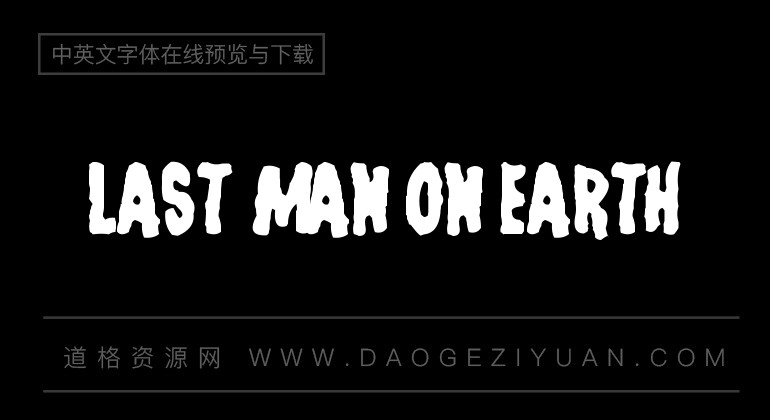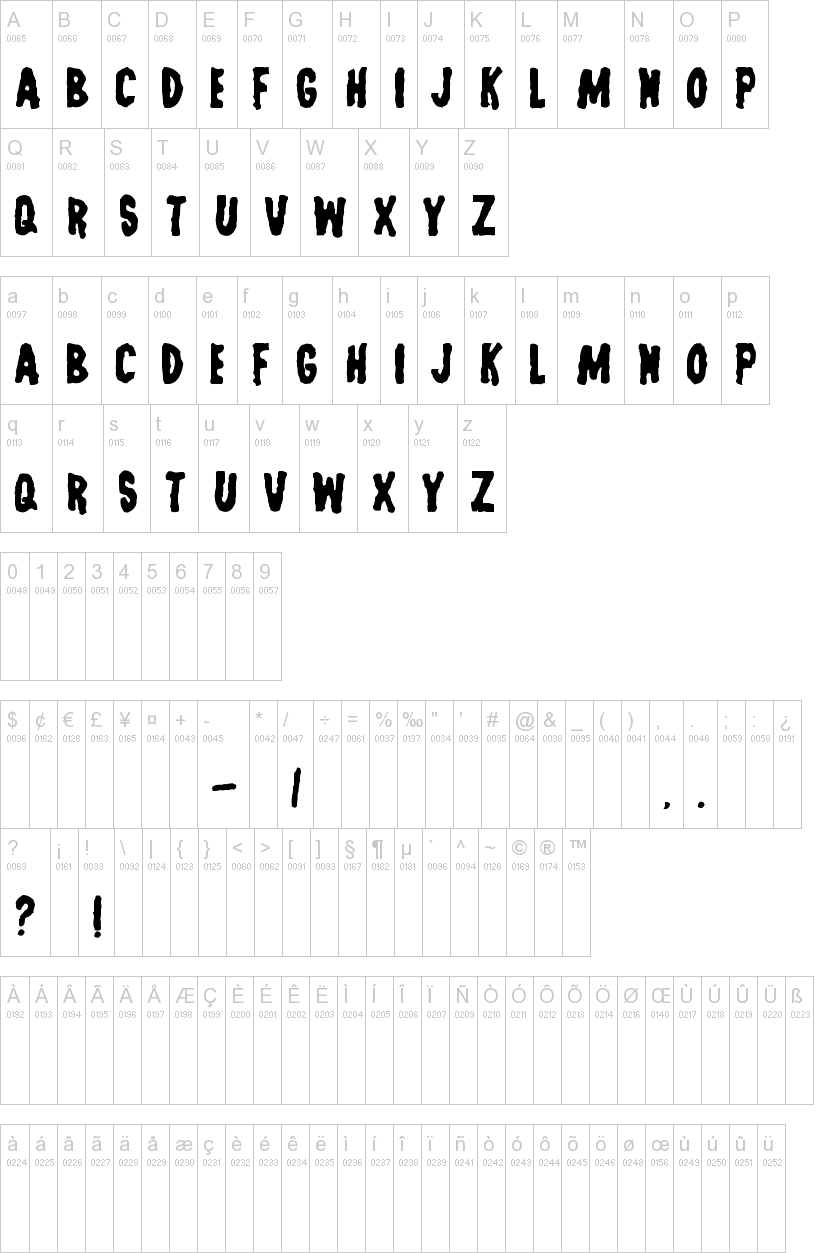
Last Man on Earth
"Last Man on Earth" 字体是一种基于手写风格的字体,具有独特的艺术感和自然感。它的字母形状非常不规则,每个字母都有自己独特的风格和特征。字体的笔画是通过手写或数字绘图软件制作而成的,使其看起来非常自然和有机。 该字体主要用于设计和艺术创作中,常见于海报、广告、音乐封面等各种场合。它的手写风格让设计感更为生动,能够吸引人的目光。由于每个字母都有自己独特的风格和特征,所以该字体在设计中非常具有表现力和创意性。 总的来说,“Last Man on Earth” 字体是一种非常具有个性和艺术感的字体,可以为各种设计作品增添独特的风格和个性。
Last Man on Earth是一款非常不错的手写艺术字体,具有很好的视觉感,适合于文化类的宣传设计、商业类品牌的广告和产品包装设计以及个性化文字排版等较多场景。